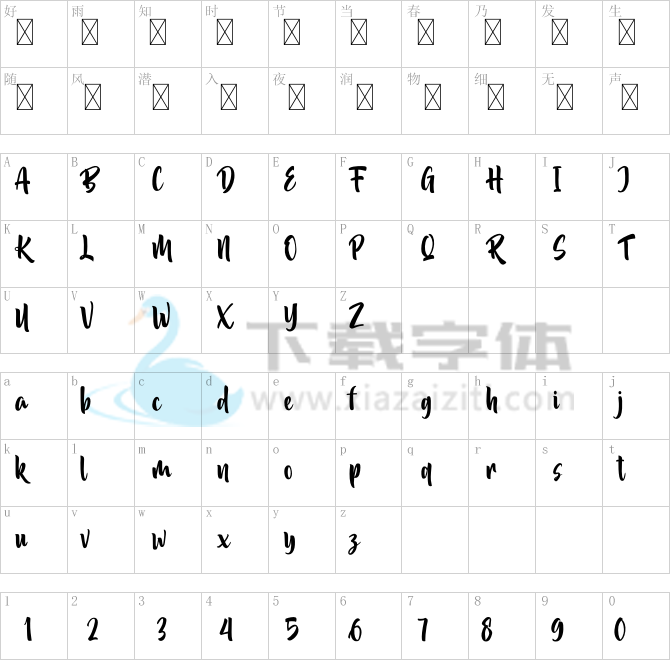
Akidan Hatory.otf字体下载,这款字体结构工整、笔画清晰,兼顾美观与易读性,适用于标题、正文、海报、包装、LOGO 等多种场景。字形优雅稳定,风格百搭耐看,适配日常排版与创意设计,让文字呈现更舒适、更具质感。Akidan Hatory.otf字体下载一笔一画,皆是细节,以均衡的比例、流畅的线条打造舒适视觉体验,字形端正大气,风格简约现代。无论是商业设计、品牌宣传还是日常排版,都能轻松驾驭,让文字更有格调与力量。Akidan Hatory.otf字体下载字体下载。
Akidan Hatory.otf图片展示
• 字体名称:Akidan Hatory
Akidan Hatory.otf映射图